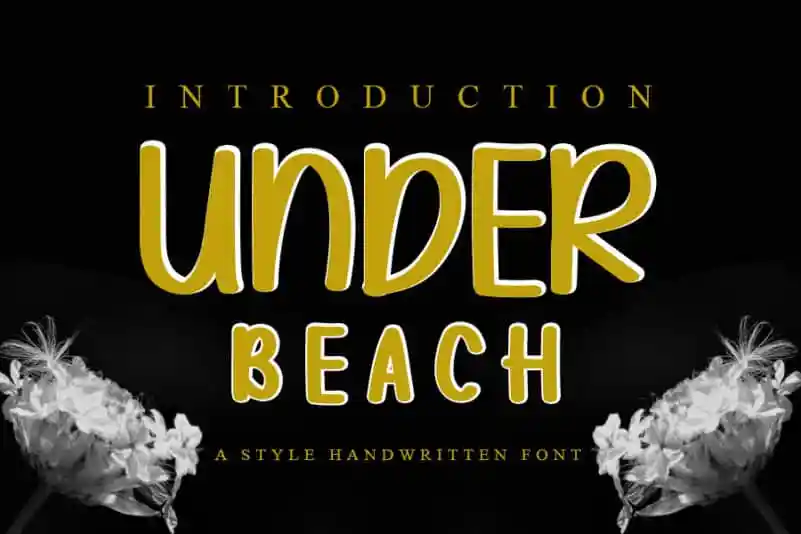
Under Beach Display Font – Download Grátis
Under Beach Display Font é uma elegante fonte escrita a mão que mantém seus influentes traços chamigráfico ao mesmo tempo contemporânea e fresca. Perfeita tanto para criações de letrinhas e títulos quanto para estilização de papelaria, essa versátil fonte cativa o pensamento criativo do usuário em uma variedade de ideias decorativas. Ideal para aquelas pessoas que buscam uma personalidade única na sua designação visual, esse é um excelente aditivo ao seu estoque de fontes. Seja você designer gráfico, editor de imagens ou simplesmente alguém que valoriza a expressão artística em seus trabalhos, Under Beach Display Font certamente encaixa-se no seu projeto de forma suave e elegante.